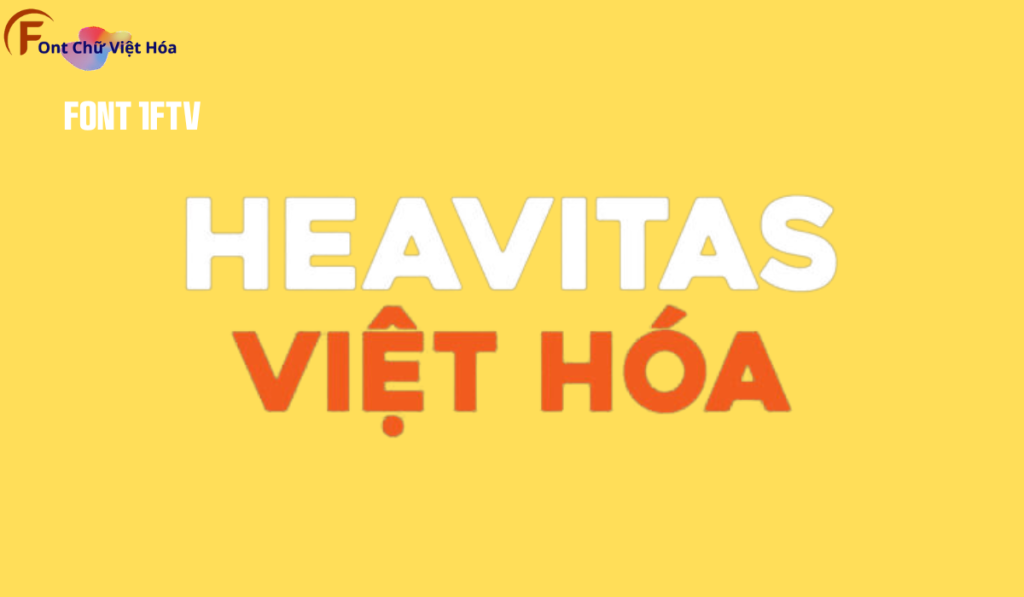
Font 1FTV Heavitas
Kiểu chữ: Sans-serif
Font 1FTV Heavitas là một font chữ nổi bật thuộc bộ 1FTV, được thiết kế với phong cách sans-serif không chân mạnh mẽ và đậm nét. Font này có kiểu dáng hiện đại, cứng cáp với độ dày chữ cao, giúp tạo ra sự ấn tượng rõ rệt trong các thiết kế đồ họa. Một trong những đặc điểm nổi bật của 1FTV Heavitas là khả năng truyền tải thông điệp mạnh mẽ, dễ đọc và đặc biệt phù hợp cho các tiêu đề, poster, và các thiết kế quảng cáo cần sự thu hút mạnh mẽ. Ngoài ra, font chữ này đã được Việt hóa, mang lại sự tiện lợi cho các nhà thiết kế trong nước.